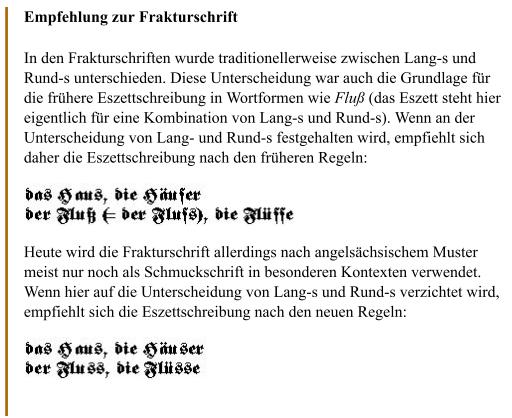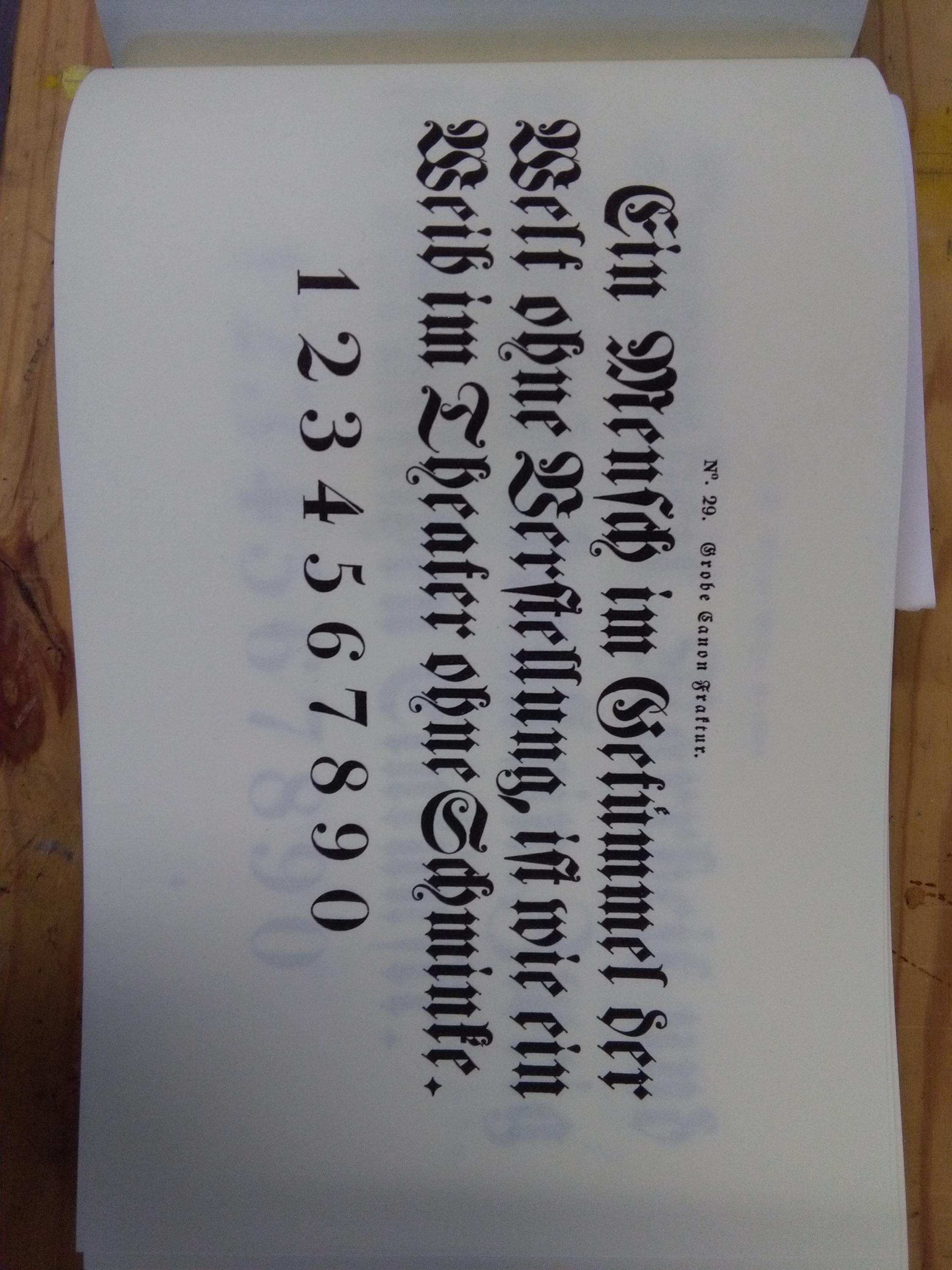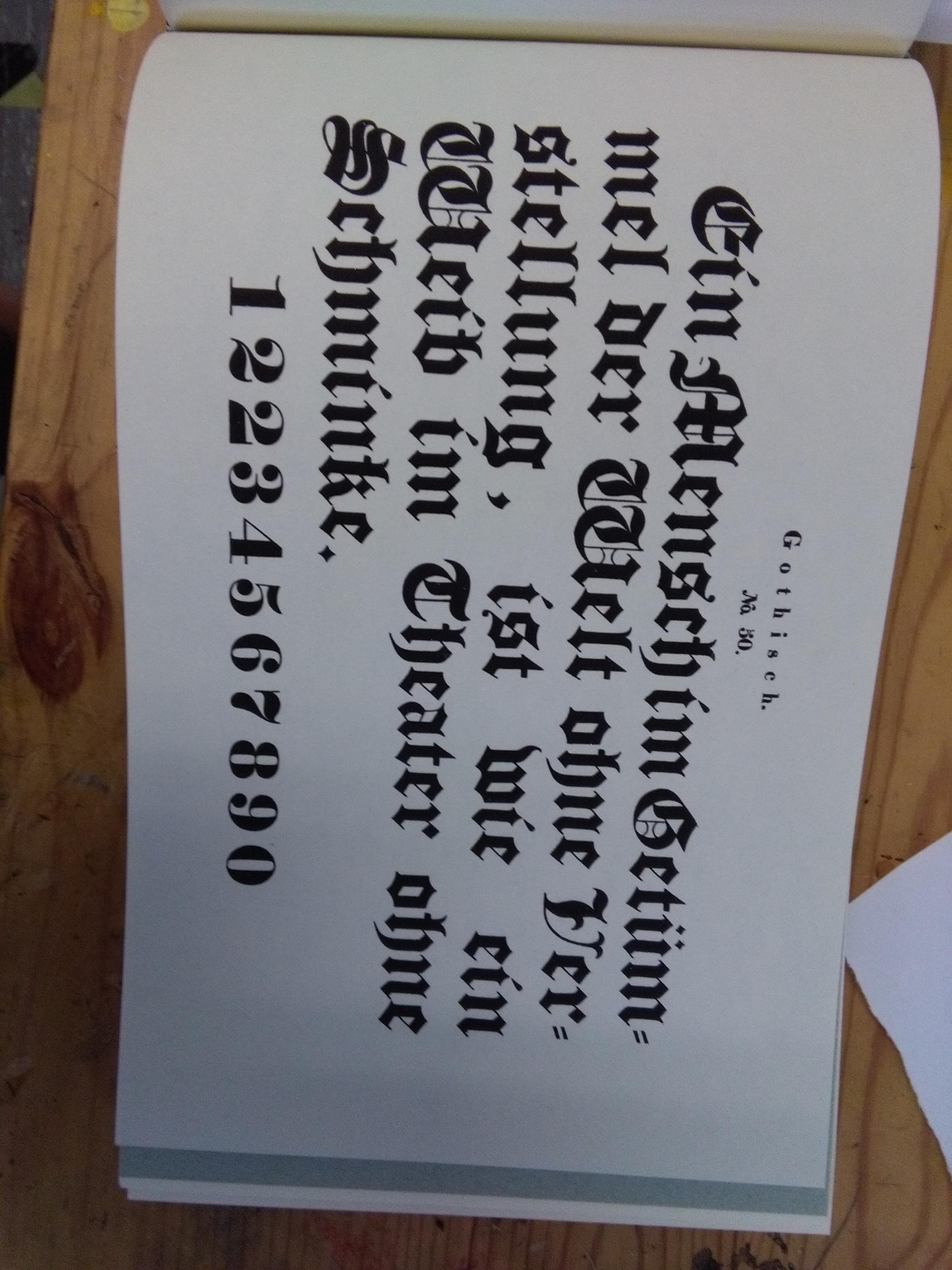
Jüngst habe ich einen Aufsatz von Herbert E. Brekle im Internet gefunden mit dem Titel »Versuch einer linguistisch begründeten Fassung der Gebrauchsregeln für das lange ſ und das runde s«:
Leider kann ich derzeit Joshuas Wiki-Artikel über die ſ-/s-Regeln nicht finden, sonst hätte ich den Aufsatz dort verlinkt.
Hier ist er noch (in einer Version, die ich größtenteils verbrochen habe) und hier in Joshuas Fassung – zumindest als Diskussionsgrundlage.
Ansonsten bin ich überrascht, wie wenig Neues mir der verlinkte Artikel verraten konnte und wo ich sogar zusätliche Informationen habe – wohl vor allem deshalb, da man dank Internet heute viel leichter an gewisse Informationen gelangen kann. Zum Beispiel habe ich in mindestens einem Wörterbuch auch z zusammen mit p und t auf der Liste der Konsonanten gefunden, vor denen das lange s steht, und von meinen Wörterbüchern schreiben alle Aſbeſt.
Ich stimme aber auf jeden Fall mit dem Autor überein, dass die Regeln in alten Wörterbüchern grauenvoll strukturiert und unnötig wiederholend sind.
Aus: »Die Neuregelung der deutschen Rechtschreibung« von Peter Gallmann und Horst Sitta
Mich wundert es, dass Peter Gallmann und Horst Sitta als Befürworter der Rechtschreibreform von 1996 nicht die Schreibung mit ſs anstatt ß empfehlen, wie es bis Anfang des 20. Jahrhunderts in Österreich gehandhabt wurde.
Wundert mich auch, zumal die Heysesche S-Schreibung, die 1879 in Österreich-Ungarn eingeführt wurde mit ſs und die Adelungsche mit ß die in Preußebn bevorzugt wurde gleich nahezu gleich alt sind.
und mit der neuen Rechtschreibung ist man ja von Adelung nach Heyse gewechselt.
Mich nicht. Im Kontext ist es doch eindeutig. Die Schreibung ſs macht nur dann Sinn, wenn auch sonst ein langes s benutzt wird. Um diesen Fall geht es aber nicht, wie sie eindeutig sagen: »Wenn hier auf die Unterscheidung von Lang-s und Rund-s verzichtet wird …«.
Also eine recht klare Logik:
• Wir haben kein ſ
• wir nutzen aktuelle Rechtschreibung
• ergo: wir schreiben Fluss.
Dem stimme ich zu und ich möchte ergänzend anmerken, dass ja auch Häuser empfohlen wird, wo nach allen historischen Regeln ein langes s genutzt wurde. Wenn sie Häuſer, aber Fluss empfohlen hätten, dann läge Grund zur Verwunderung vor.
Die Verwunderung des Fadeneröffners lag aber wohl bei der Version mit langem s, wo entgegen Heyse die Schreibung nach Adelung empfohlen wird, Heyse nur in Klammern ...
Mich wundert es in der Tat, dass bei Schreibung mit langem ſ die Adelung’sche s-Schreibung empfohlen wird.
Achso. Also es geht um »die Häuſer am Fluß«. Aber warum die Verwunderung? Die Schreibung mit ß ist die etablierte Schreibweise des 20. Jahrhunderts und somit in gewisser Weise die letztgültige »traditionelle« Form, die wohl deshalb empfohlen wird.
In den Frakturschriften wurde tradtionell zwischen Lang-s und Rund-s unterschieden. Diese Unterscheidung war auch die Grundlage für die frühere Eszettschreibung in Wortformen wie Fluß (das Eszett steht hier eigentlich für eine Kombination von Lang-s und Rund-s). Wenn an der Unterscheidung von Lang- und Rund-s festgehalten wird, empfiehlt sich daher die Eszettschreibung nach den früheren Regeln.
In: Gallmann/Sitta: Die Neuregelung der deutschen Rechtschreibung, S. 3.
Ich finde die oben zitierte Argumentation auch nicht schlüssig. Die Entscheidung zwischen alter und reformierter Rechtschreibung ist eine sprachliche, die zwischen einer Antiqua- und einer Frakturschrift eine typografische Entscheidung.
Wenn man die Unterscheidung zwischen Rund-s und Lang-s beibehält, muss das nicht mit dem alten Wechsel zwischen ſſ und ß nach kurzem Vokal (Flüſſe, Fluß) verbunden werden. Die Idee, dass Lang-s nicht final stehen kann, ist ja auch in der Buchstabenkombination ſs (Flüſſe, Fluſs) nach Heyse erhalten, die der aktuellen Rechtschreibung entspricht. Der Duden (Rechtschreibung, 26. Aufl., 2013, S. 114) empfiehlt diese Variante.
Der Gedanke liegt aber nahe, dass diese Gattung als eher fremdländisch/weniger deutsch angesehen wurde und dann entsprechend gesetzt wurde.
Aber wohl auch diese Assoziation, falls sie vorhanden war (was ich keinesfalls anzweifeln möchte, aber auch nicht bestätigen kann) ging mit der Zeit verloren, wenn man sich das folgende  Plakat der DVP (zur Reichstagswahl von 1920) anschaut, die kein